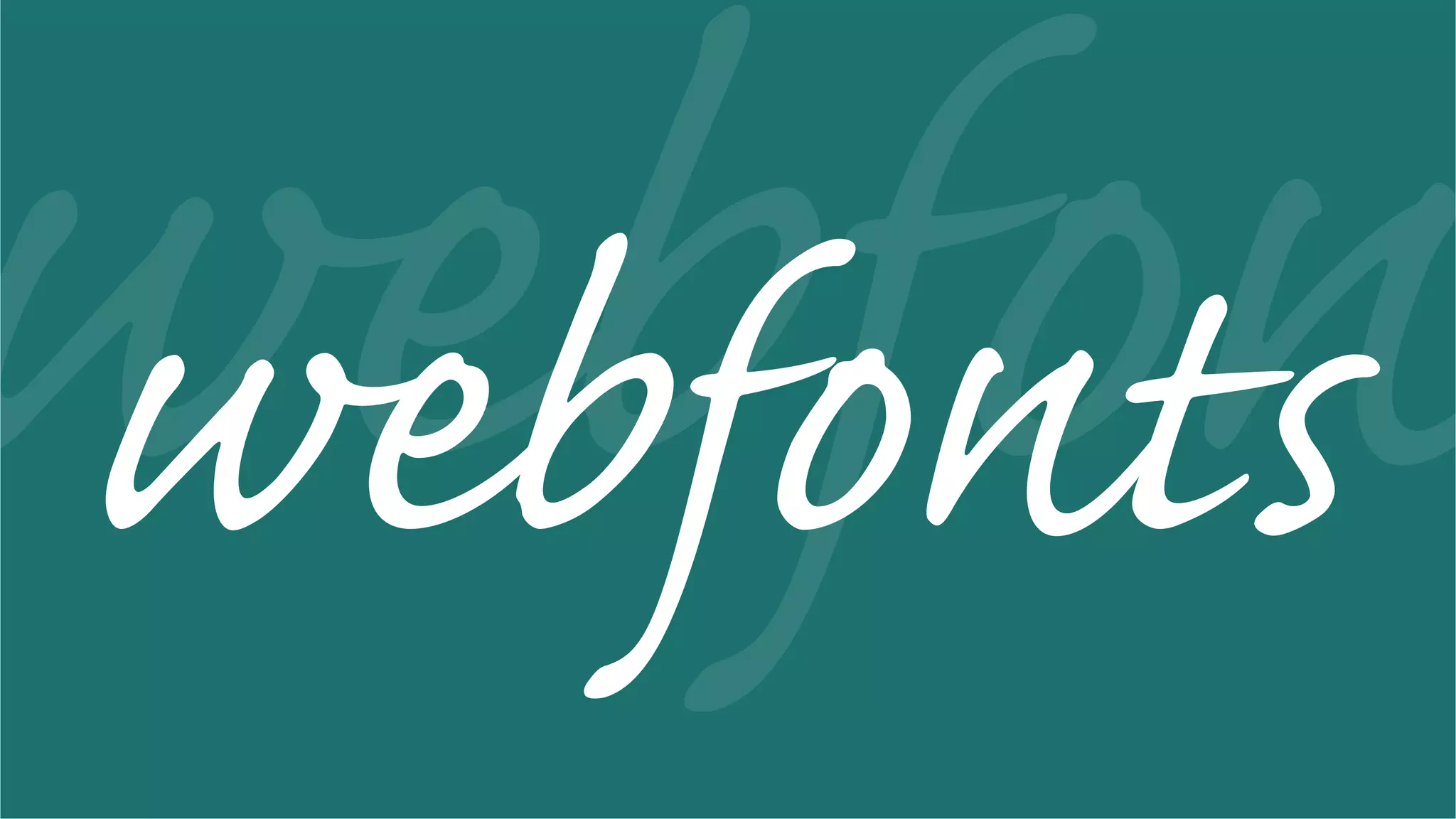
Wo findet man den richtigen Webfont
Free Webfonts
Kostenpflichtige Webfonts
Typografie im Web
Was kann „schiefgehen“?
Unterschied zwischen Leserlichkeit und Lesbarkeit
Leserlichkeit sind typografische Faktoren
•	Schriftart
•	Schrift-Größe
•	Buchstabenabstand
•	Zeilenabstand
•	Zeilenlänge
Lesbarkeit
•	Rechtschreibfehler
•	falsche Interpunktion
•	Bandwurmsätze
•	zu viele Füllwörter
Abstand & Weißraum
„Zu viel Abstand gibt es eigentlich nicht!“ 1
Weißraum
•	„Weißraum bezeichnet die Gesamtheit der Abstands- und Leerflächen in einem Layout.“ 1
Abstand
•	Spaltenabstand, Zeilenabstand, Randabstand
Dies ist ein sehr sehr sehr sehr
sehr lange Headline
Dies ist ein gutes Beispiel für
die Leserlichkeit
Headline
Der Zeilenabstand ist hier
zu gering, die Leserlichkeit
wird dadurch verringert.
Der Zeilenabstand ist hier
zu groß. Die Headline wird
nicht mehr als zusammen-
hängend wahrgenommen.
Zeilenlänge & Spalten